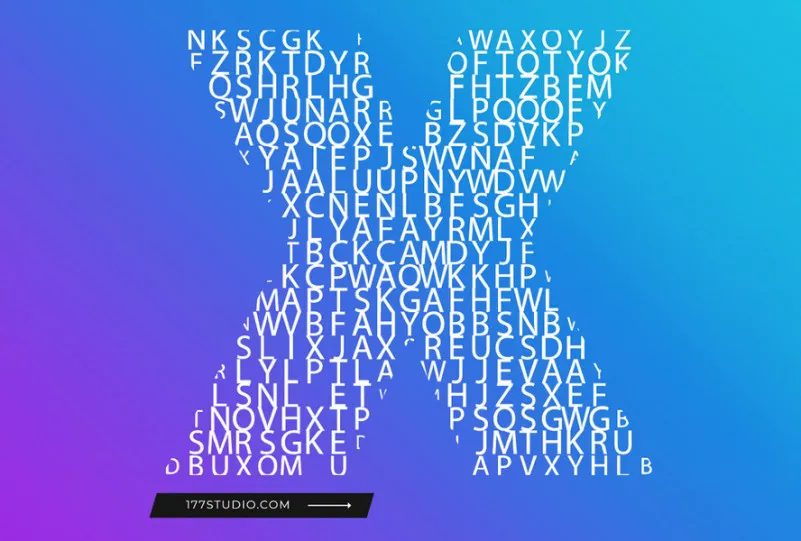
Character with Text Font – Fonte Grátis
Character with Text Font
A fonte “Character with Text Font” é uma escolha ideal para qualquer projeto que busque desempenho visual impressionante. Inspirada nos espaços entre as letras, essa fonte display contém texturas e detalhes incríveis que permitem um resultado de texto envolvente. Essa característica única permite criar logotipos atraentes, combinações de ilustração, headlines poderosas, rótulos para lojas, panfletos, embalagens, adesivos e mais, com uma aparência vibrante e detalhada. Perfeita para estilos modernos de design gráfico, essa font é perfeitamente adaptável a diversos formatos de mídia visual. É perfeito para transformar mensagens em experiências visuais impactantes sem perder os detalhes que tornam cada palavra um verdadeiro desafio à ser decifrada. O resultado final cria uma atmosfera envolvente, que convida o público a mergulhar na fonte e nas mensagens que ela destaca. Inspirado no design elegante do 177Studio, essa font é uma escolha inovadora para aqueles que desejam deixar marcas em seus projetos visuais. Não importa se você está criando um logotipo exclusivo ou desenvolvendo uma campanha digital impressionante, “Character with Text Font” oferece a oportunidade de estabelecer o seu design como uma experiência visual imersiva e memorável.